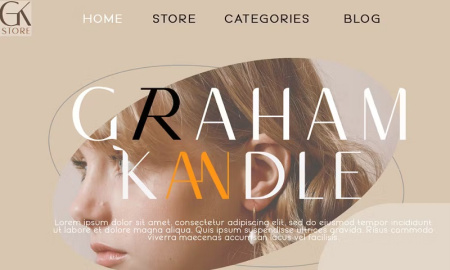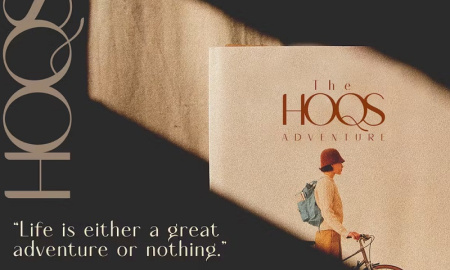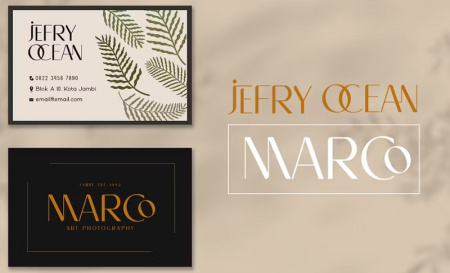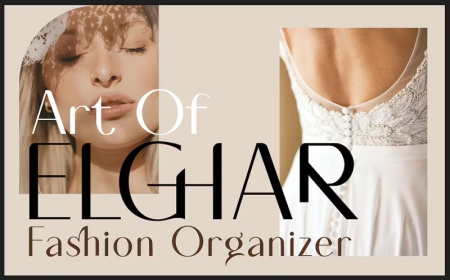
دانلود رایگان فونت انگلیسی Weglly Hauston از جی اف ایکس دانلود که به صورت کاملا رایگان برای دانلود قرار گرفته شده است. یک فونت نمایشگر مدرن و زیبا است که با تغییرات حروف مانند جایگزین و لیگاتور ایجاد شده است. آن را ترکیب کنید و طرح تایپوگرافی عالی خود را بسازید!